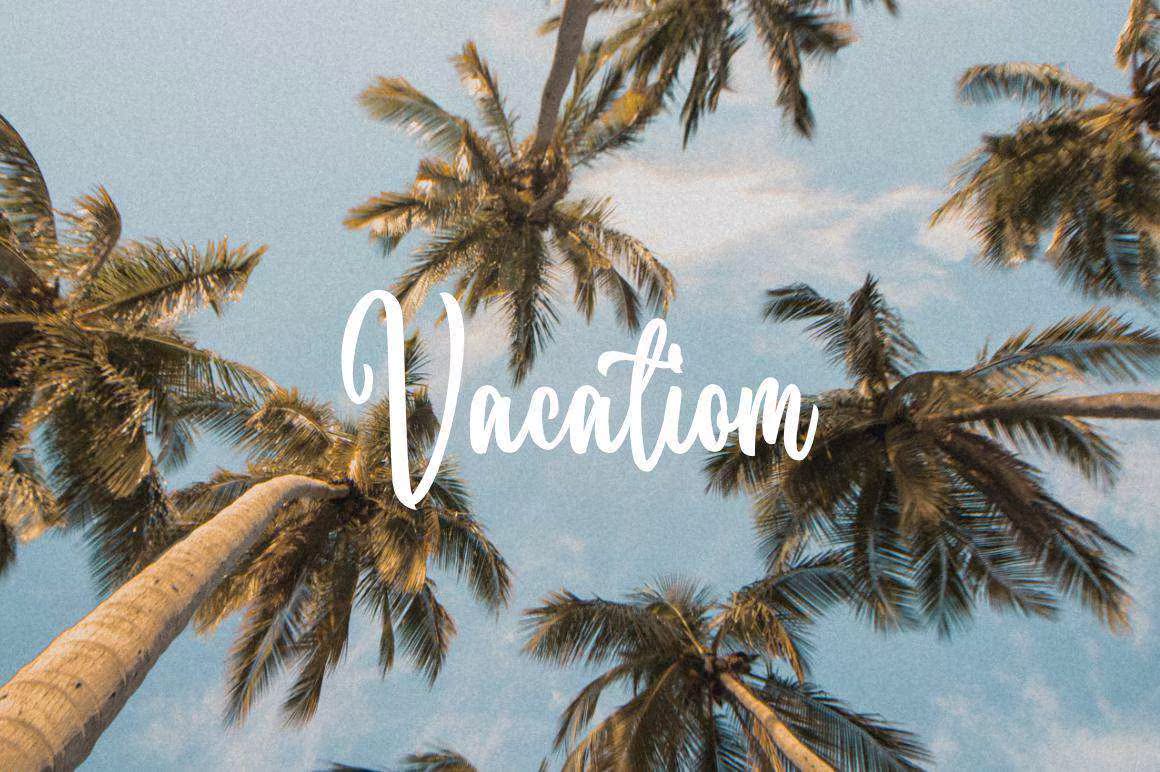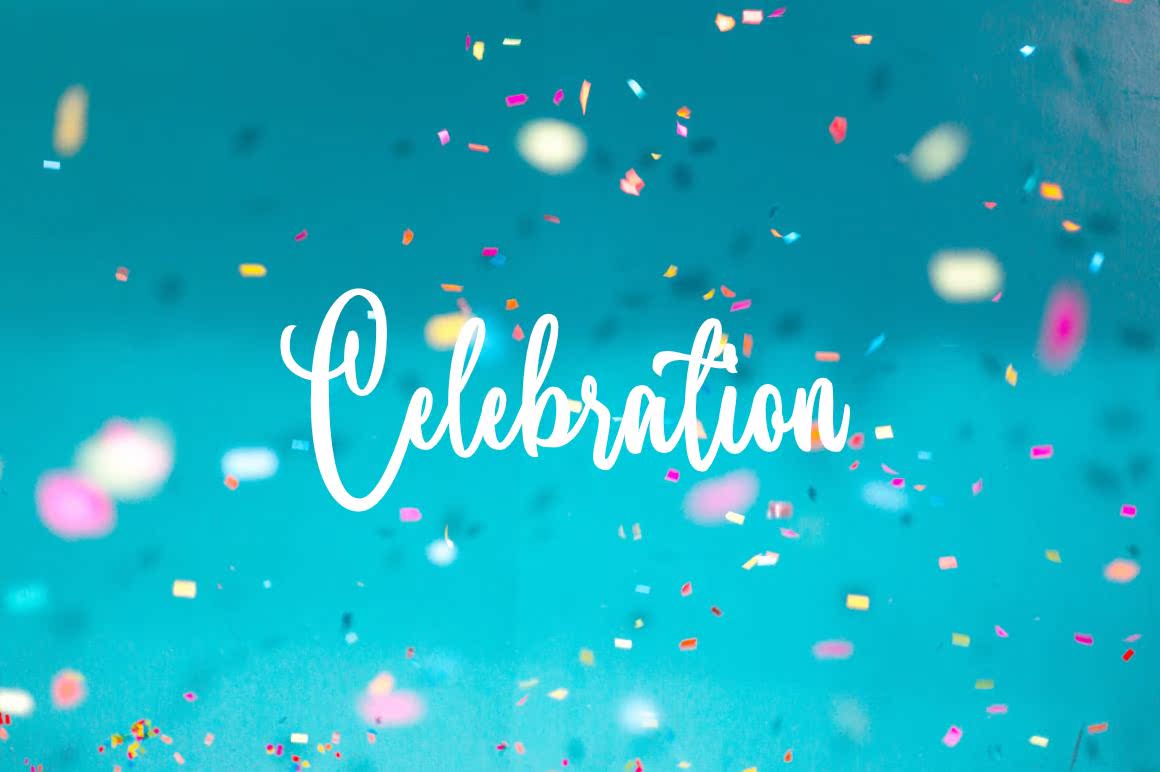
请使用带有临时大气和特殊电缆形式的Book Kissanelegant Scription Font。此Font的设计旨在增强项目的美观。请使用Book Kissanelegant Scription Font,这意味着您可以访问Glyph和Swashese!请使用带有临时大气和特殊电缆形式的Book Kissanelegant Scription Font。此Font的设计旨在增强项目的美观。请使用Book Kissanelegant Scription Font,这意味着您可以访问Glyph和Swashese!